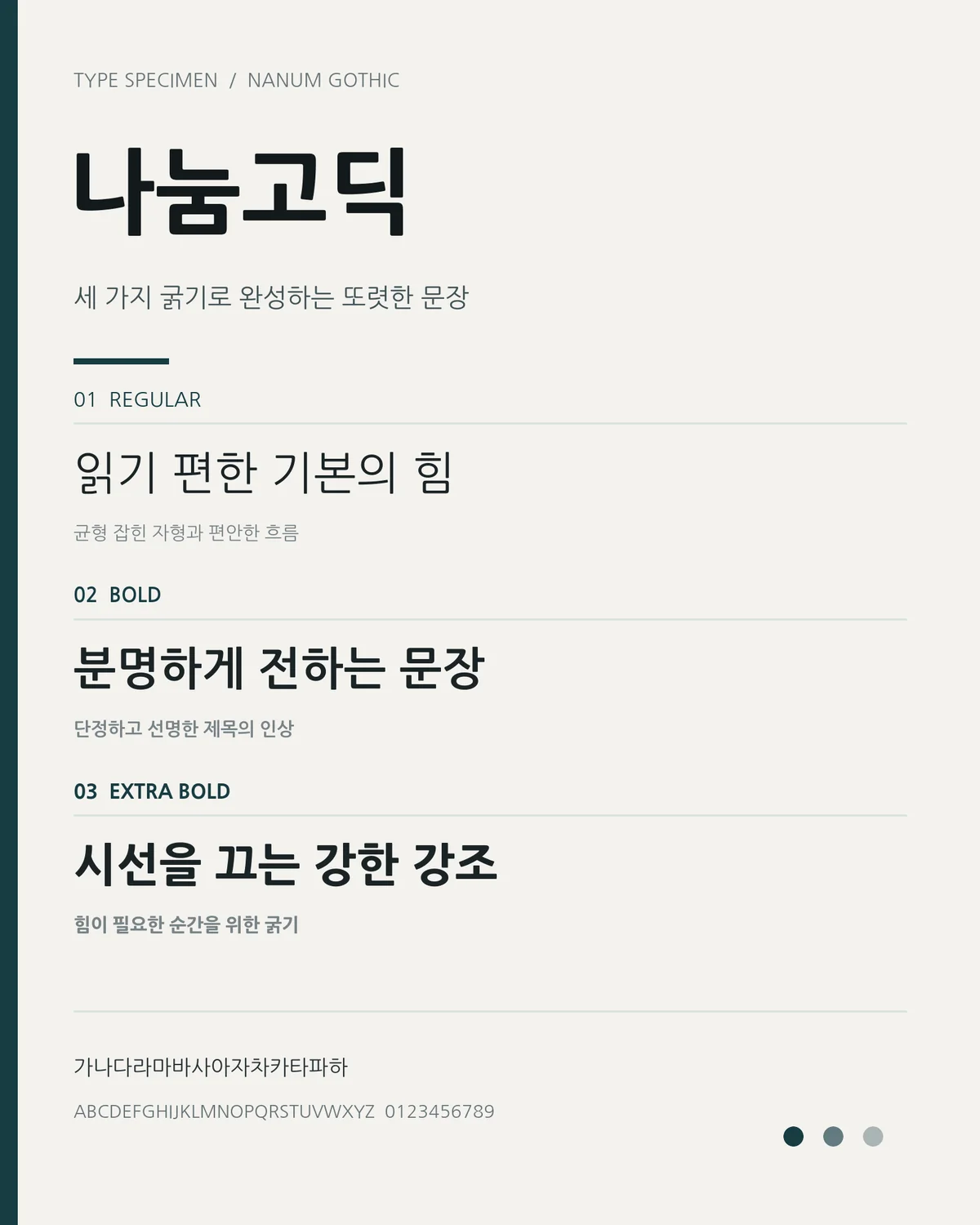
나눔고딕 — 네이버에서 배포하는 무료 폰트입니다. 부드러운 굴림의 인상을 바탕으로 한국적인 조형미와 현대적인 감각을 담은 고딕체
2008년 한글날, 네이버가 한글한글 아름답게 캠페인의 결과물로 나눔명조와 함께 공개한 서체입니다. 산돌커뮤니케이션이 제작했고, 저작권 걱정 없이 누구나 쓸 수 있는 한글 글꼴을 만든다는 것이 기획의 출발점이었습니다. 2010년 6월부터는 SIL 오픈 폰트 라이선스로 풀려, 수정과 재배포까지 자유로운 몇 안 되는 한글 서체가 됐습니다.
글자를 만드는 방식이 남다릅니다. 자주 쓰는 2,350자는 완성형으로 하나하나 그리고 나머지 8,822자는 조합형으로 채워 현대 한글 11,172자를 모두 지원하며, 여기에 한자 4,888자가 더해집니다. 특히 완성형 2,350자에는 화면에서 획이 계단처럼 어긋나지 않도록 손으로 힌팅을 넣었는데, 윈도우 클리어타입 환경에서 작은 글자를 또렷하게 만들기 위한 작업이었습니다.
굵기는 2008년 Regular와 Bold로 시작해 이듬해 ExtraBold, 2011년 Light가 차례로 더해졌습니다. 나중에 나온 Light는 자주 쓰는 한글 2,350자만 담고 있어서, 그 밖의 글자는 다른 굵기로 써야 합니다. 형태는 굴림의 부드러운 인상을 이어받아 획 끝을 둥글게 다듬은 민부리 계열이고, 낱자는 폭보다 높이가 커서 세로로 선 편입니다. 워낙 널리 쓰여 호환성이 중요한 자리에서는 가장 안전한 선택이지만, 바로 그 이유로 브랜드의 개성을 드러내야 하는 작업에서는 인상이 묻히기 쉽습니다.